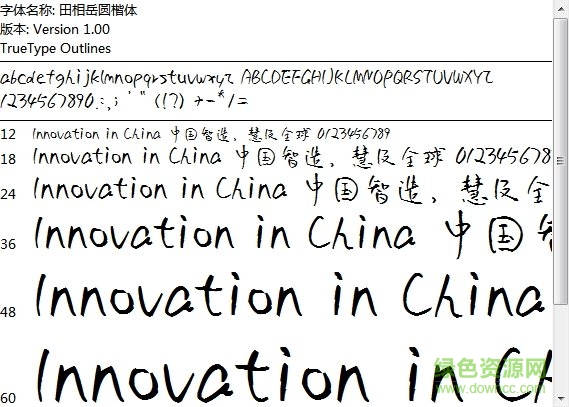
田相岳圓楷體是田氏系列字體推出的一款古典中文字體,讓楷體書(shū)法更顯圓潤(rùn),創(chuàng)意般的造型給大家更來(lái)獨(dú)特審美體驗(yàn),歡迎大家來(lái)綠色資源網(wǎng)搶先嘗試!
田氏圓楷體是全新推出的一款手寫(xiě)藝術(shù)設(shè)計(jì)的字體,該字體以圓體為楷體而設(shè)計(jì),線條粗細(xì)適中,整體效果非常的出色,能夠適用于大標(biāo)題、品牌廣告宣傳等需要強(qiáng)力視覺(jué)表現(xiàn)的環(huán)境,同時(shí)也可用于藝術(shù)設(shè)計(jì)、包裝印刷、簽名設(shè)計(jì)、圖形設(shè)計(jì)等領(lǐng)域。
該字體以黑體為楷體而設(shè)計(jì),線條粗細(xì)適中,整體效果非常的出色,能夠適用于大標(biāo)題、品牌廣告宣傳等需要強(qiáng)力視覺(jué)表現(xiàn)的環(huán)境。